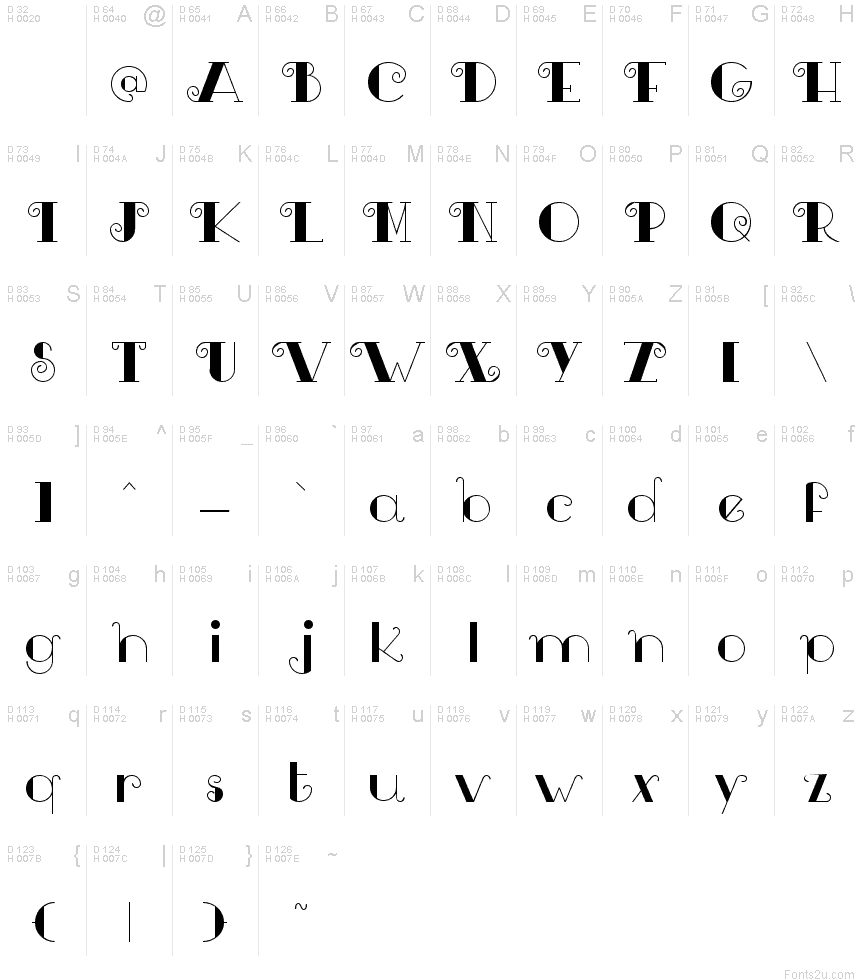
Tortillon Tryout autorstwa M. Bujardet to bezpłatny, komiksowy krój displayowy w stylu retro, z subtelnym, secesyjnym zawijasem biegnącym przez litery. Wysokie, teatralne pociągnięcia łączą się z miękkimi, okrągłymi formami, a małe, spiralne haczyki nadają czcionce klimat plakatów z dawnych lat — jest zabawna i przystępna, a przy tym pełna charakteru.
Sprawdza się wszędzie tam, gdzie tytuł ma przyciągać wzrok: na opakowaniach butikowych, w menu kawiarni, na okładkach magazynów, plakatach wydarzeń czy czołówkach filmów. Jako darmowy font, Tortillon Tryout doskonale nadaje się do krótkich nagłówków i inicjałów w formie monogramów, ponieważ zawinięte detale i wyraźny pionowy rytm mają wystarczająco dużo wyrazu, by efektownie prezentować się nawet przy kilku literach.
Tortillon Tryout